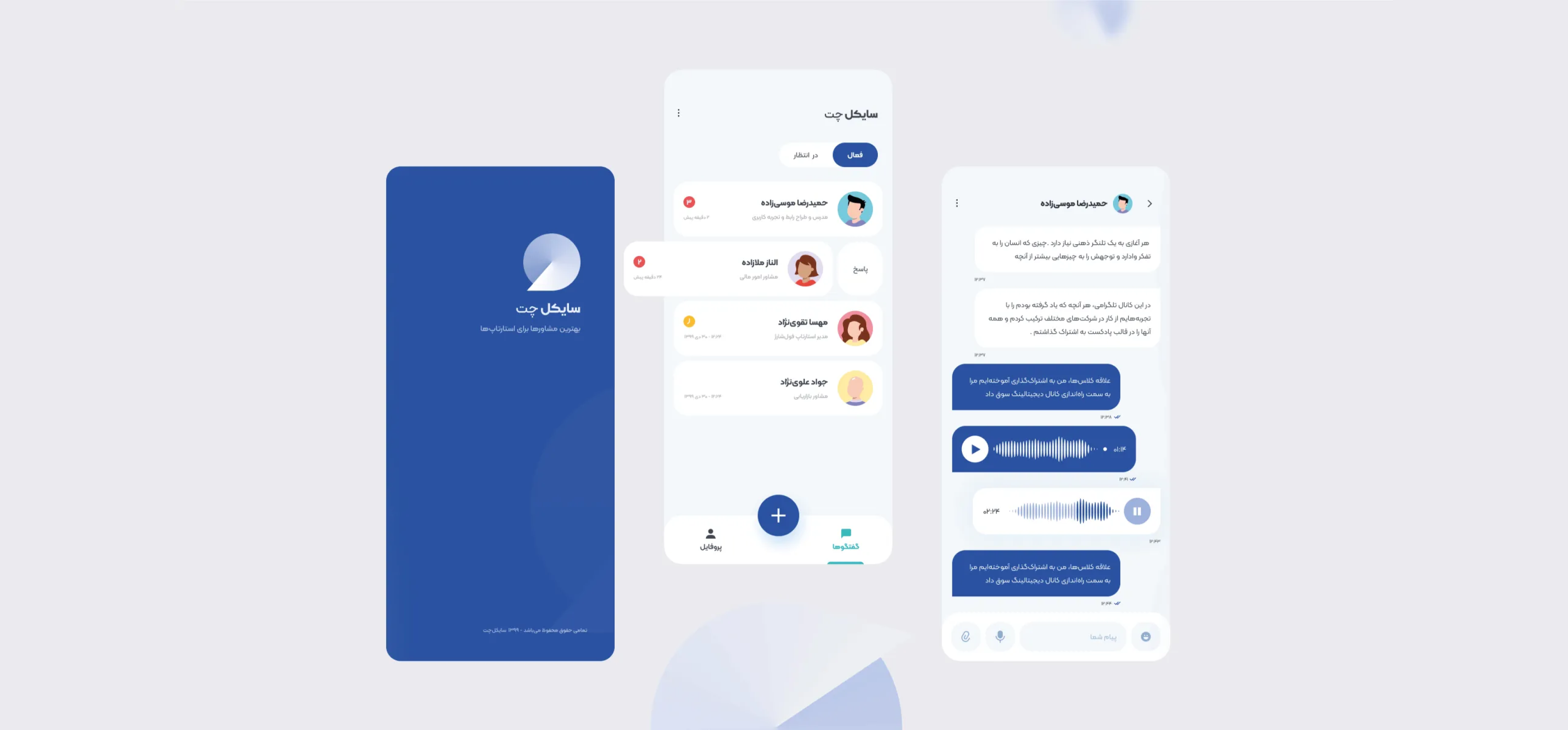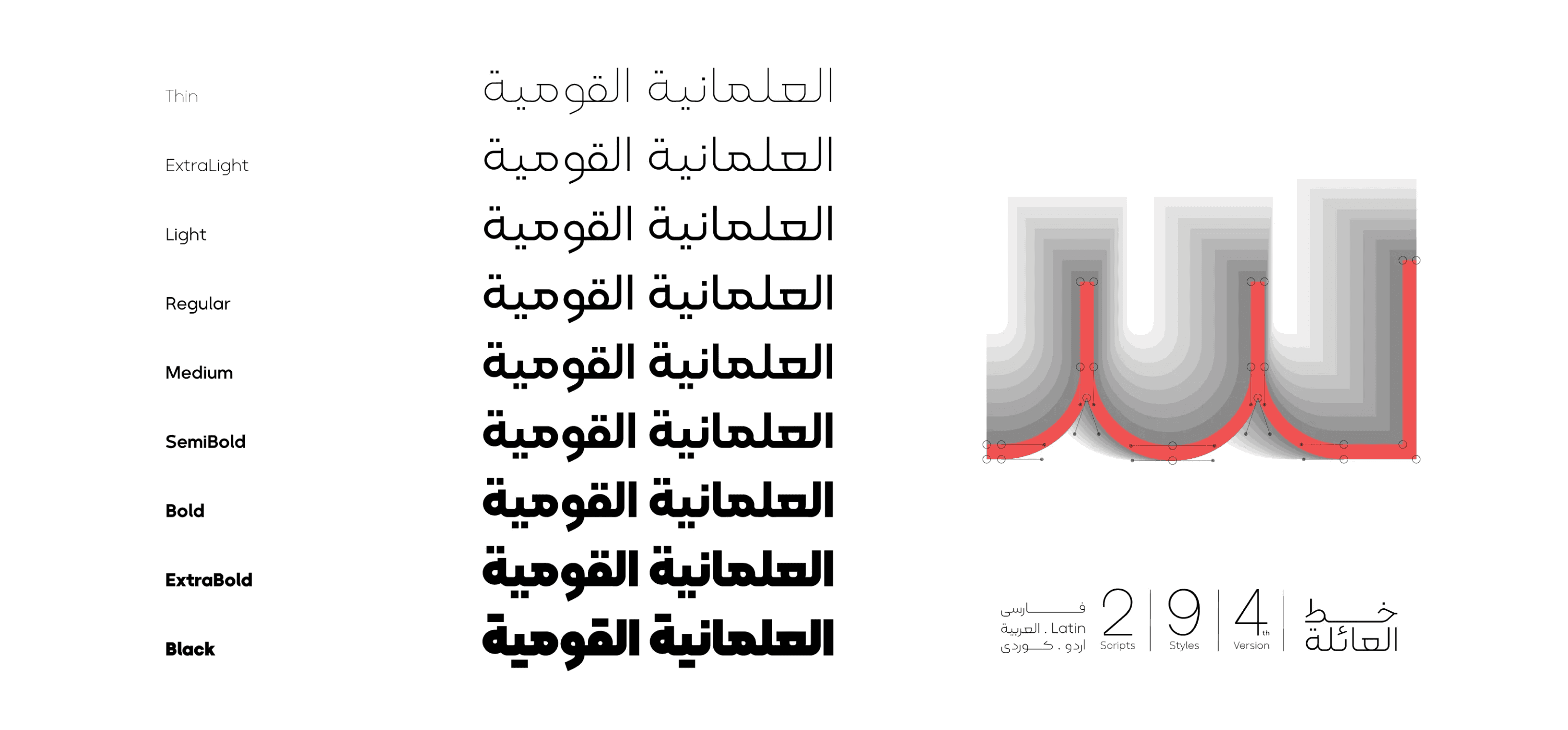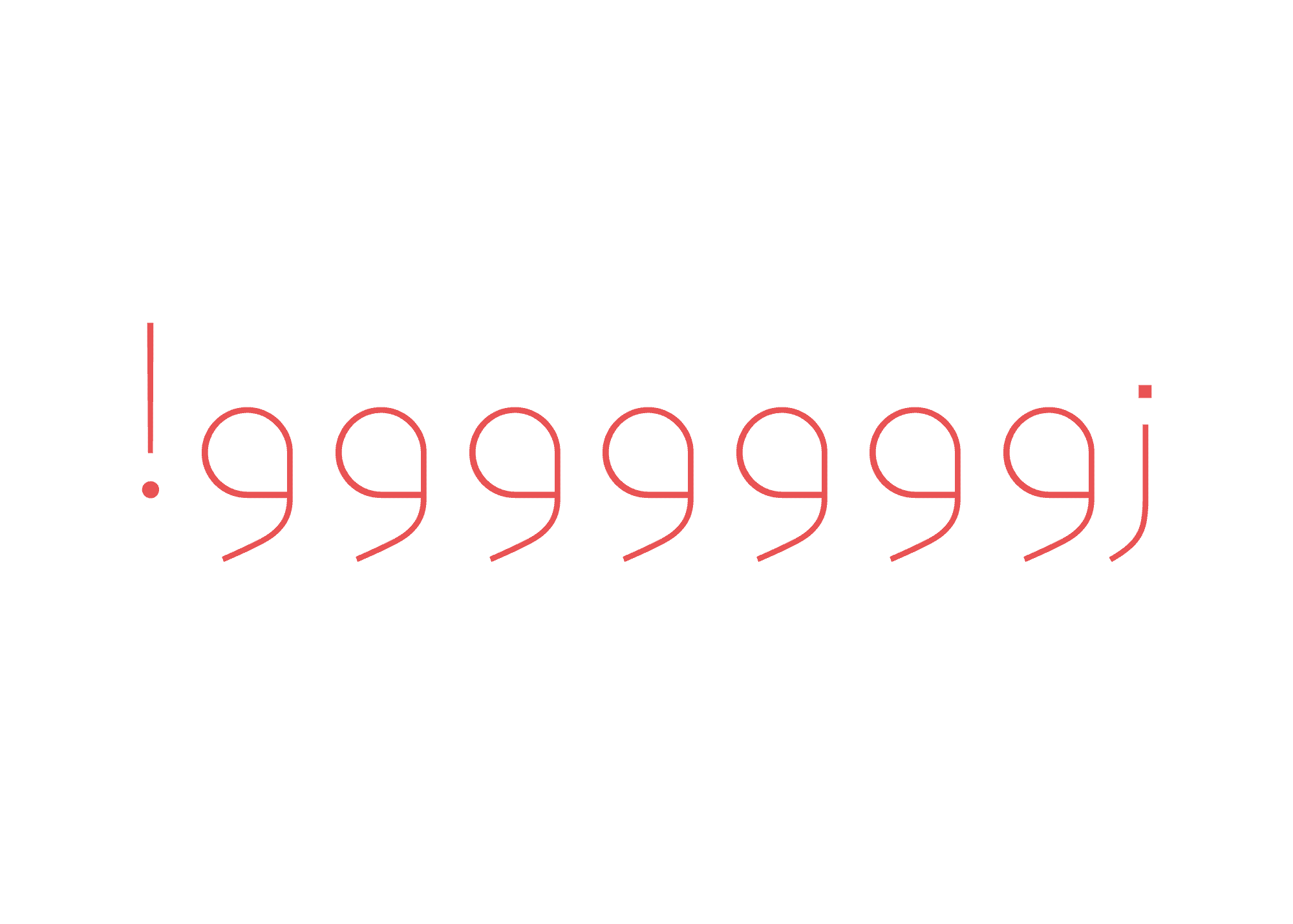
خط Kalameh يتميّز ببنية هندسية ومنظمة، حيث يُضفي تجمّد هيكل الحروف طابعًا من الانتظام والدقة.
تمنح حيويّة وطاقة هذا الخط قابلية كبيرة لاستخدامه في أغلب الأعمال الإعلانية، وخاصة لدى الشركات الناشئة والمشاريع الإبداعية والمبتكرة.
يُعد Kalameh خطًا قويًا ومتفاخرًا؛ ففي النصوص التي تهدف إلى إبراز صفات معيّنة أو تسليط الضوء على نقاط القوة والتميّز، يمنحها "Kalameh" هذه الهيبة والقوة البصرية المطلوبة.